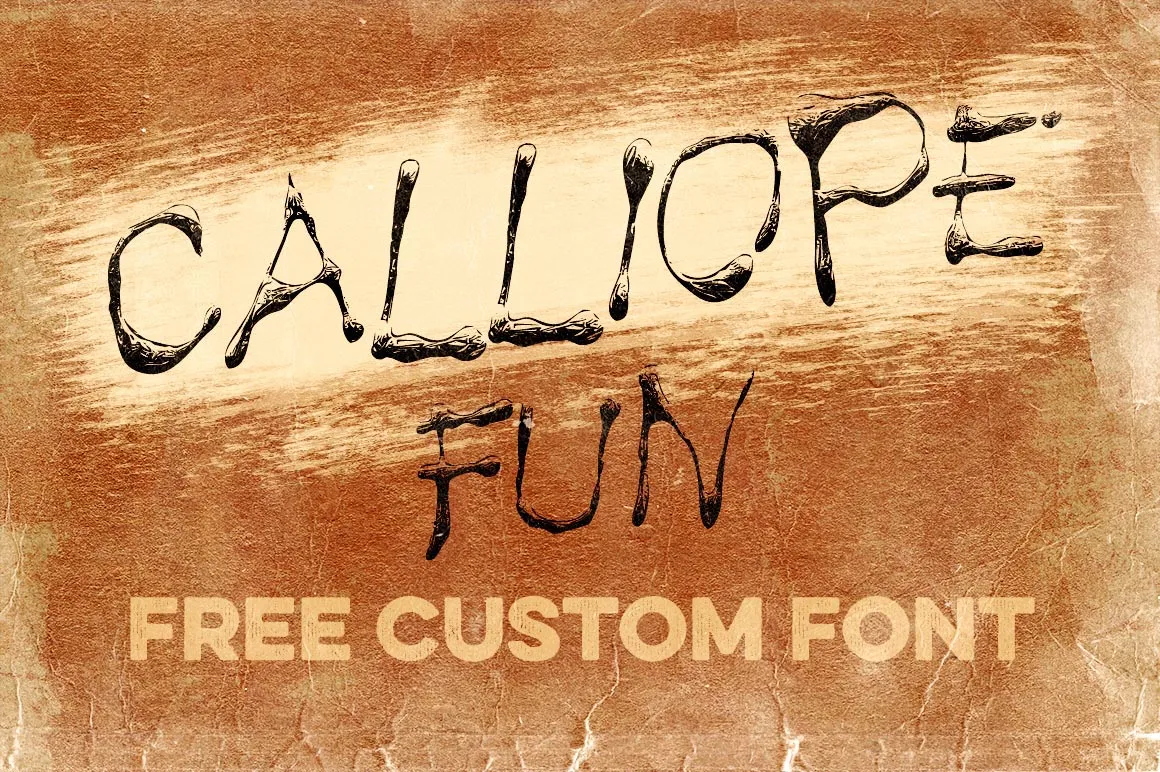
A Calliope Fun Font é uma escolha perfeita para quem busca dar um toque divertido aos seus projetos de design digital. Desenvolvida pela Cruzine Design, esta fonte tem um estilo criativo e único, ideal para inovar em sua próxima ideia gráfica ou projeto de arte digital. Seja em cartazes interativos, desenhos para crianças ou até mesmo em emojis únicos, a Calliope Fun Font traz um toque descontraído que vai destacá-lo na web ou em qualquer aplicativo. Como designer ou ilustrador, você encontrará aqui uma fonte capaz de expressar sua personalidade e criar experiências memoráveis para seus usuários finais. Descubra essa novidade divertida da Cruzine Design; ela certamente adicionará um charme especial ao seu trabalho!